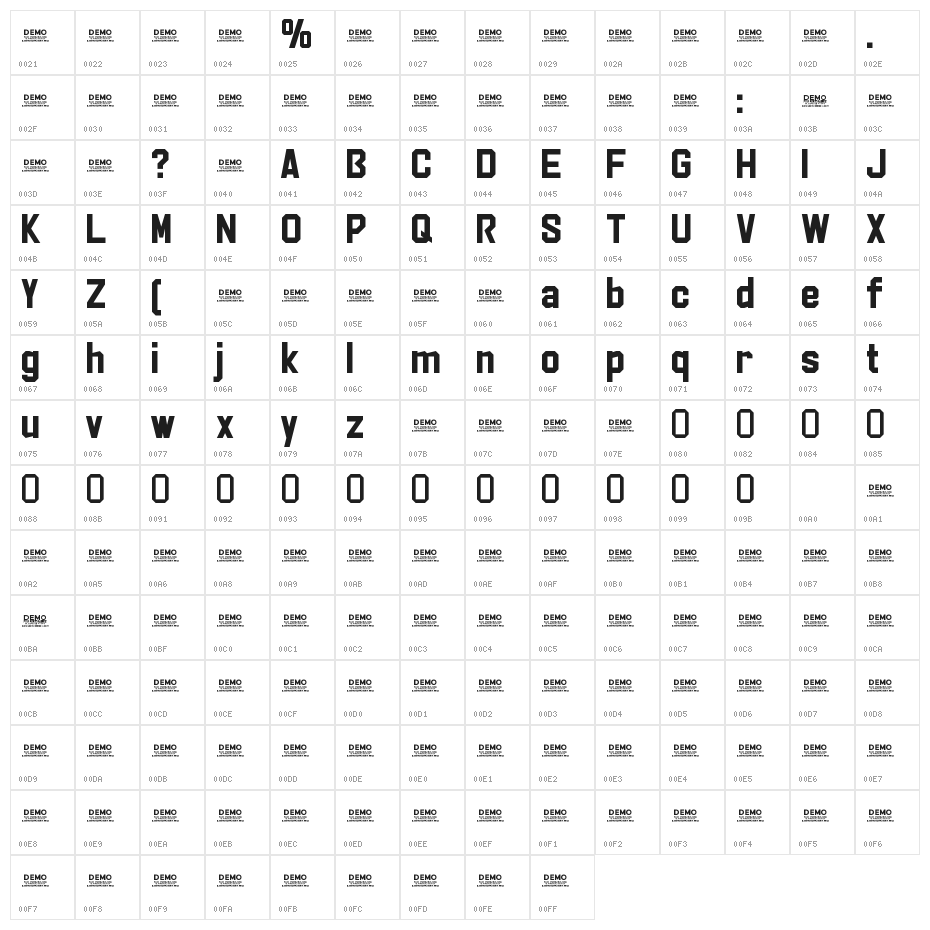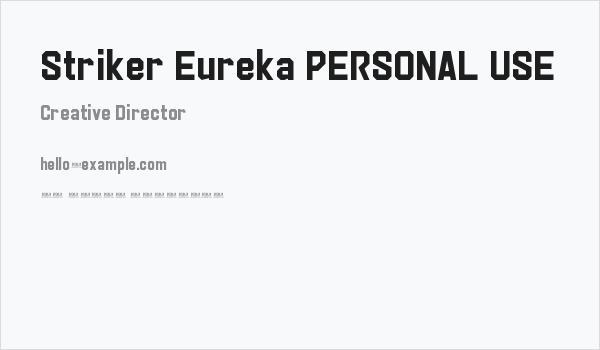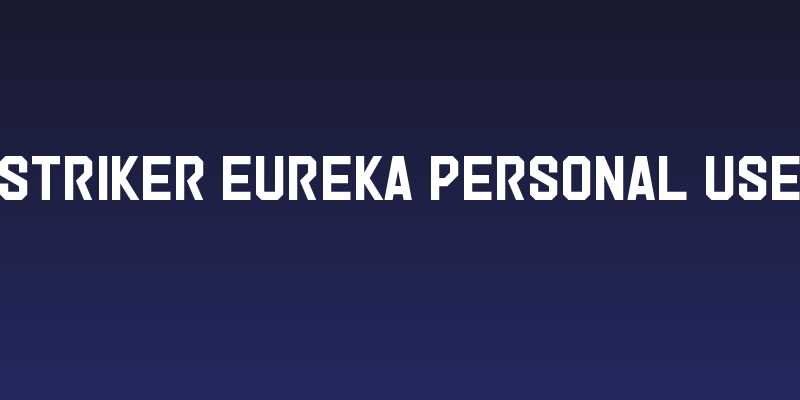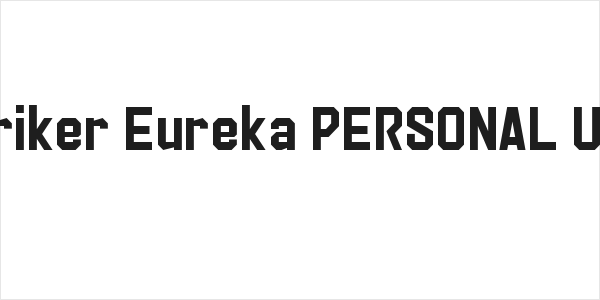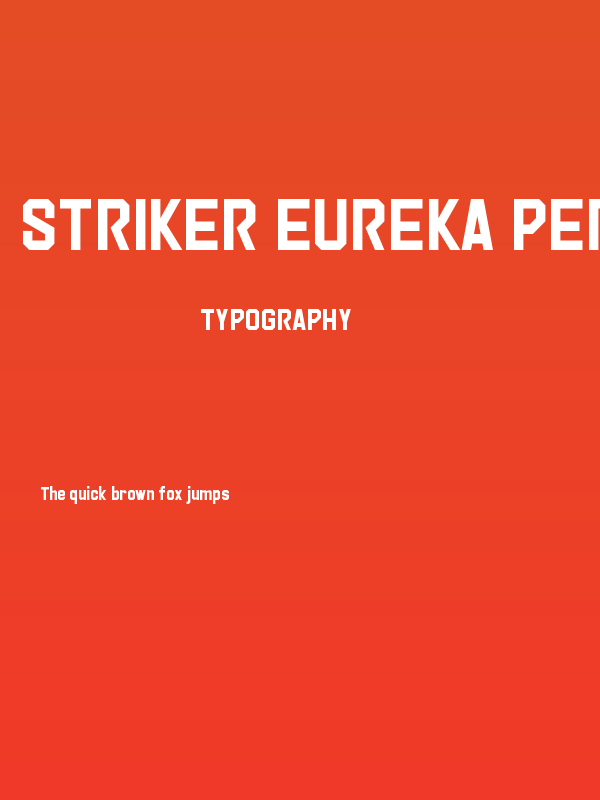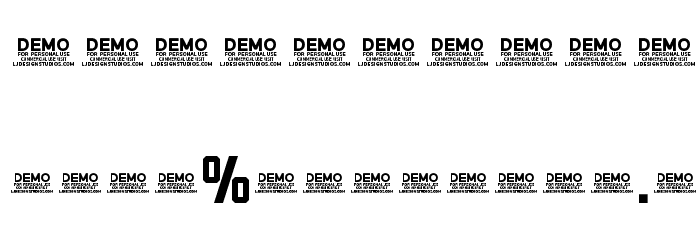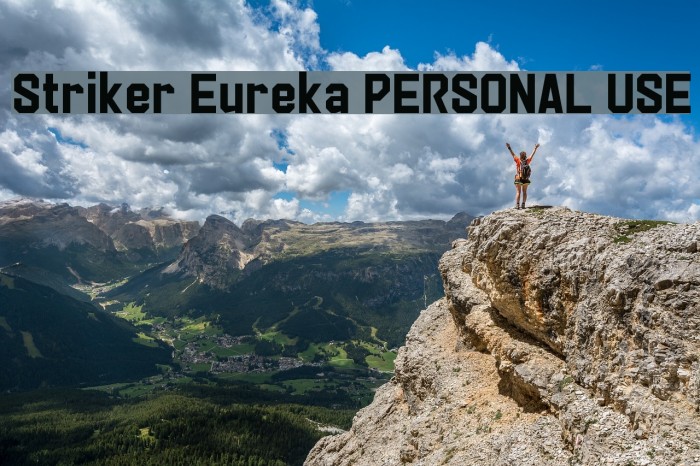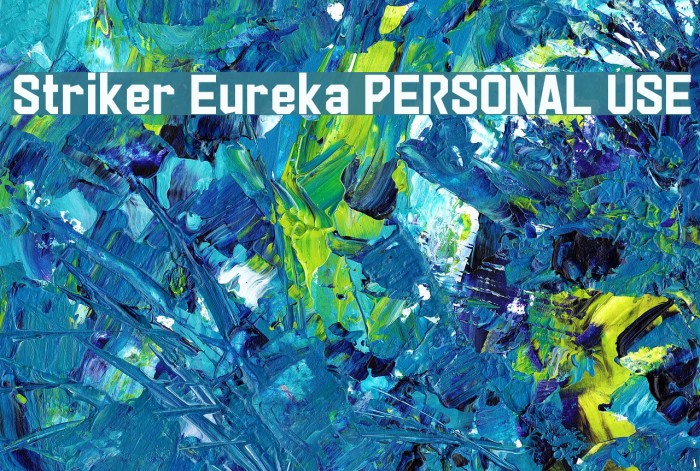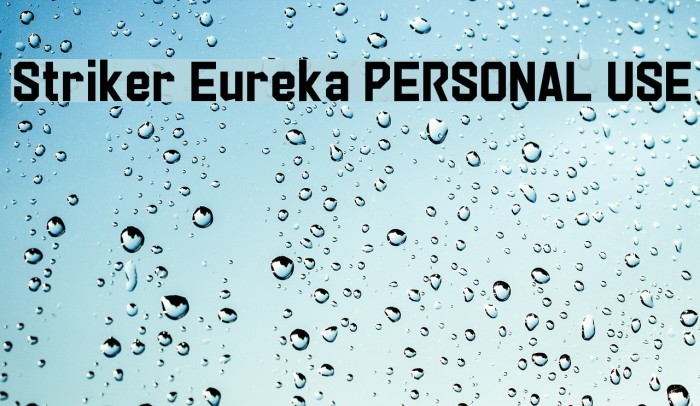
Striker Eureka PERSONAL USE Font
LJ Design Studios - Luis Jaramillo - www.ljdesignstudios.com
| Vorgeschlagene Projekte | Ideal for branding, posters, headlines, and any project requiring a strong, modern aesthetic. |